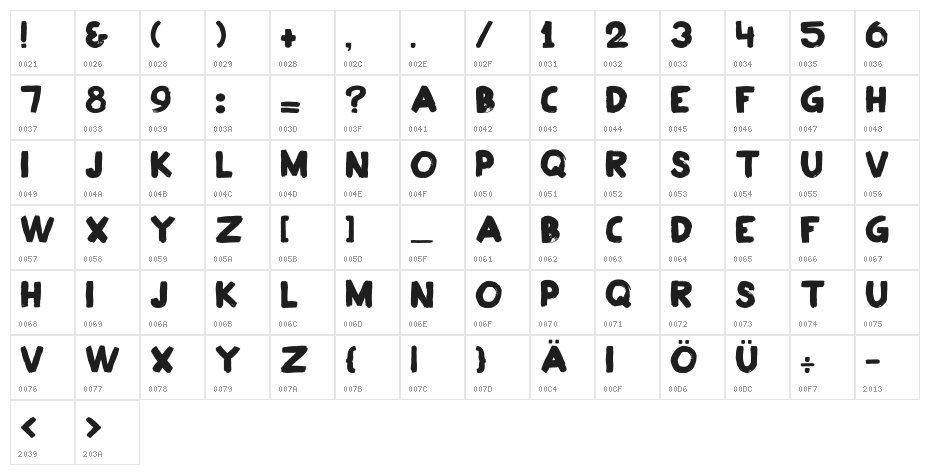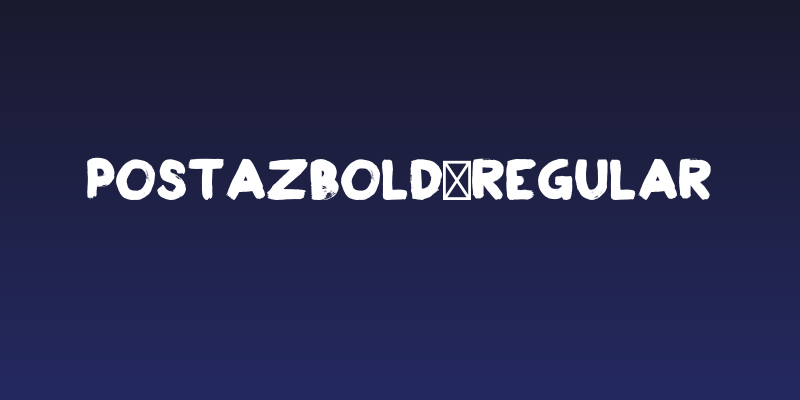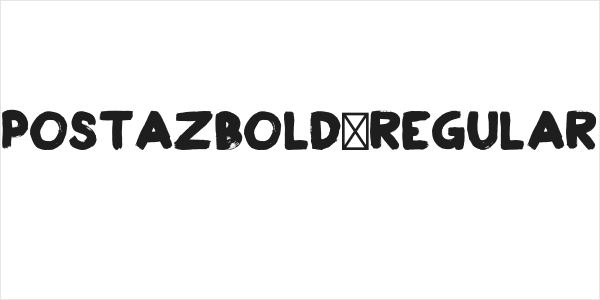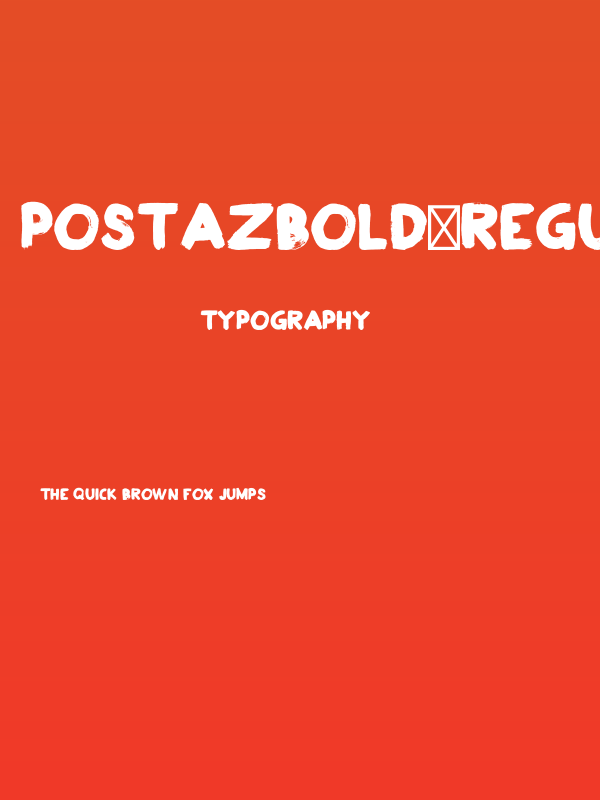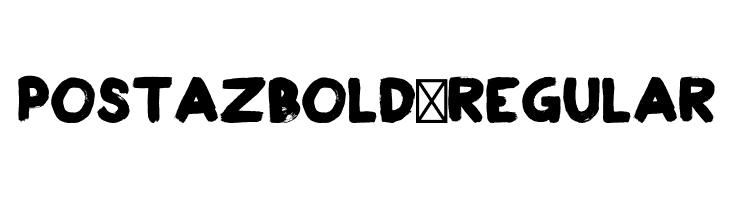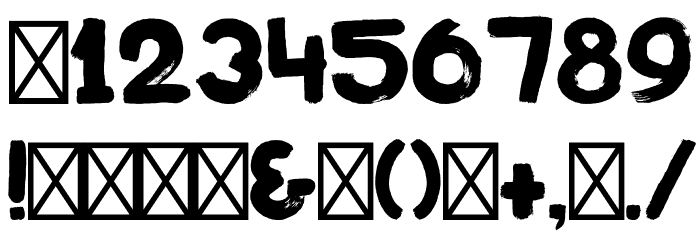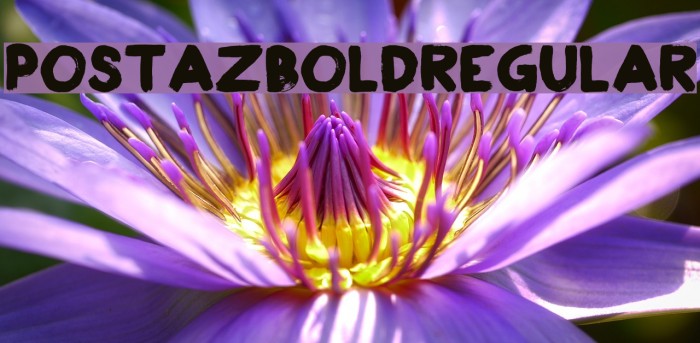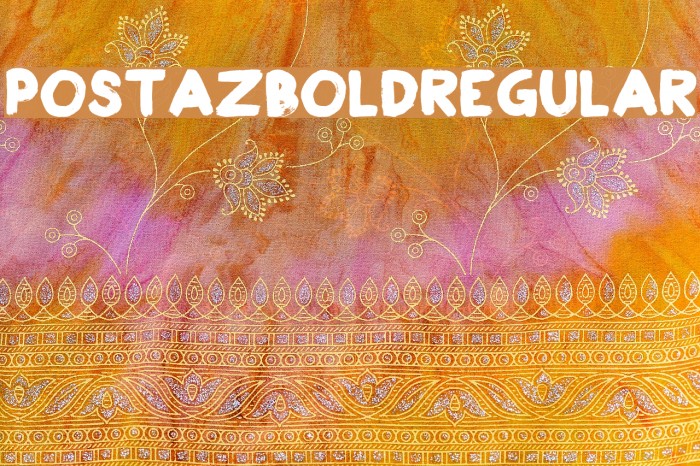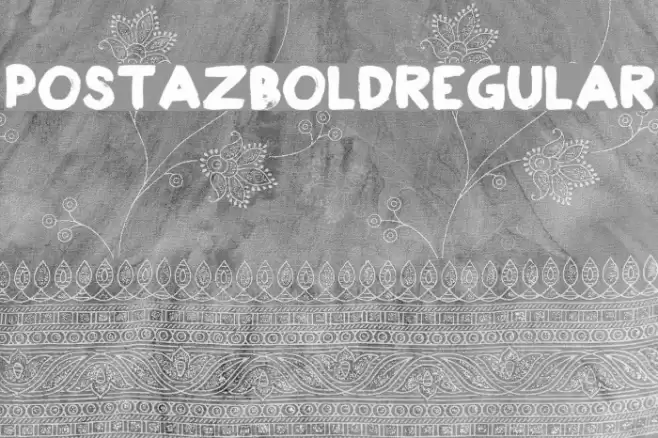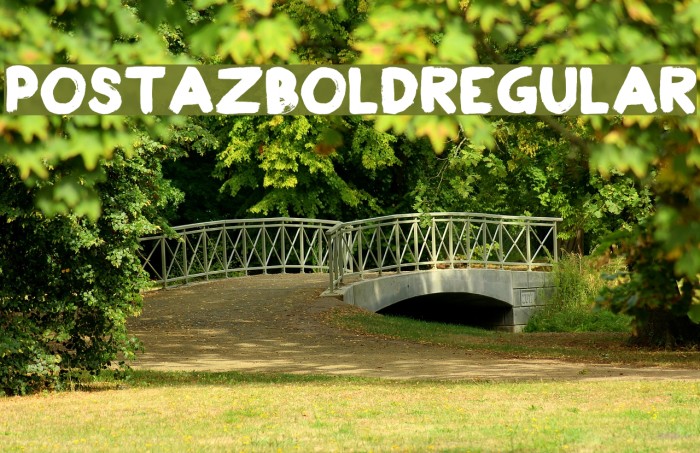
PostazBold-Regular Font
| Stile generale | Artistic, Bold, Expressive |
| Progetti proposti | Ideal for posters, branding, packaging, and any creative projects that require a bold, artistic touch. |